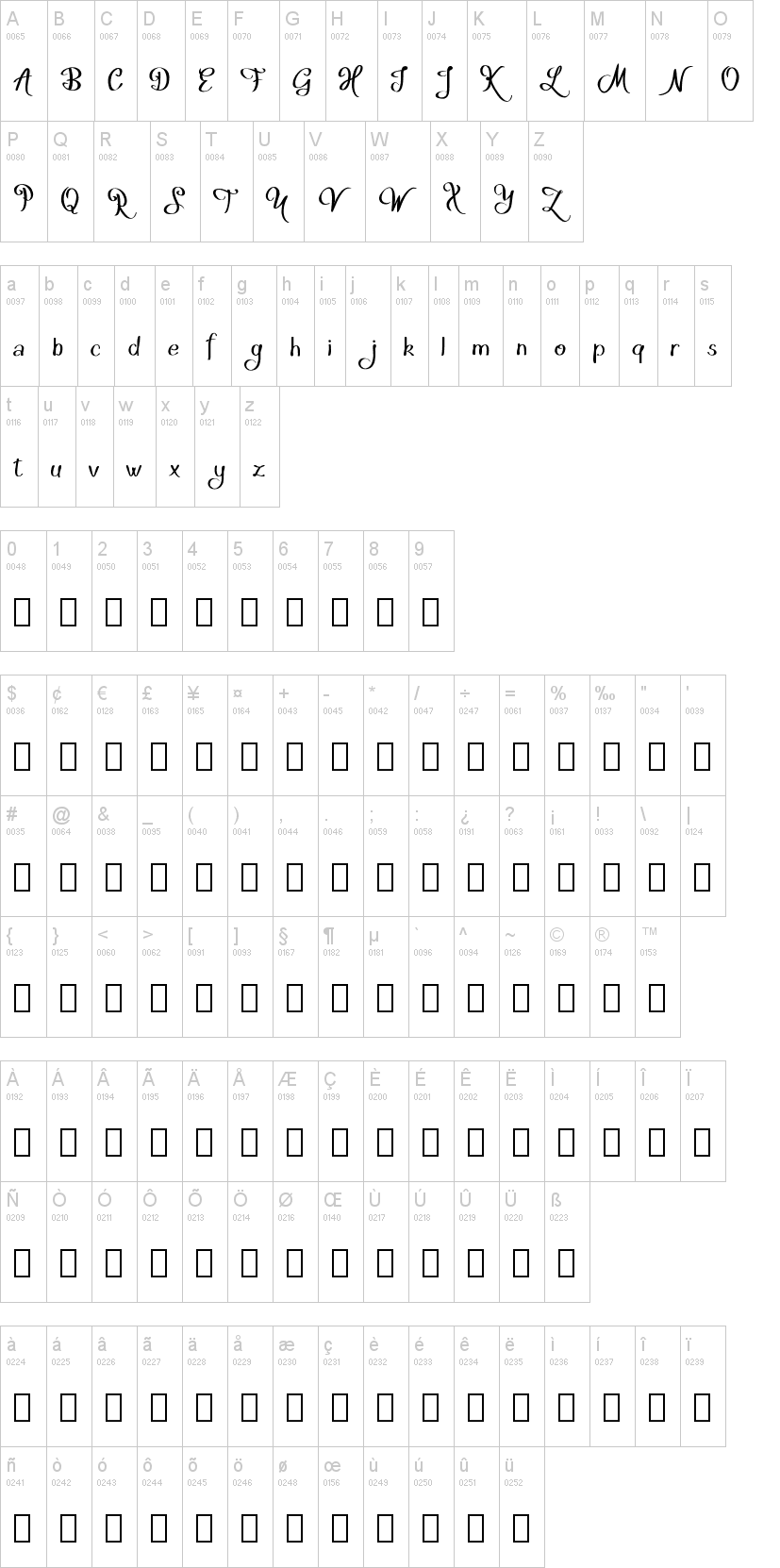
Hakyt 是一款由英国设计师 Adam Ladd 创作的字体。它是一款简洁、优雅的英文字体,适合用于标题、封面和排版文本。Hakyt 的字体特点是字母间的间距较大,这使得它的文本内容更加清晰易读。此外,Hakyt 字体还具有优秀的可读性,能够提高文本内容的易读性,使文本更加清晰易读。内容介绍
Hakyt是一款非常不错的手写艺术字体,具有很好的视觉感,适合于文化类的宣传设计、商业类品牌的广告和产品包装设计以及个性化文字排版等较多场景。